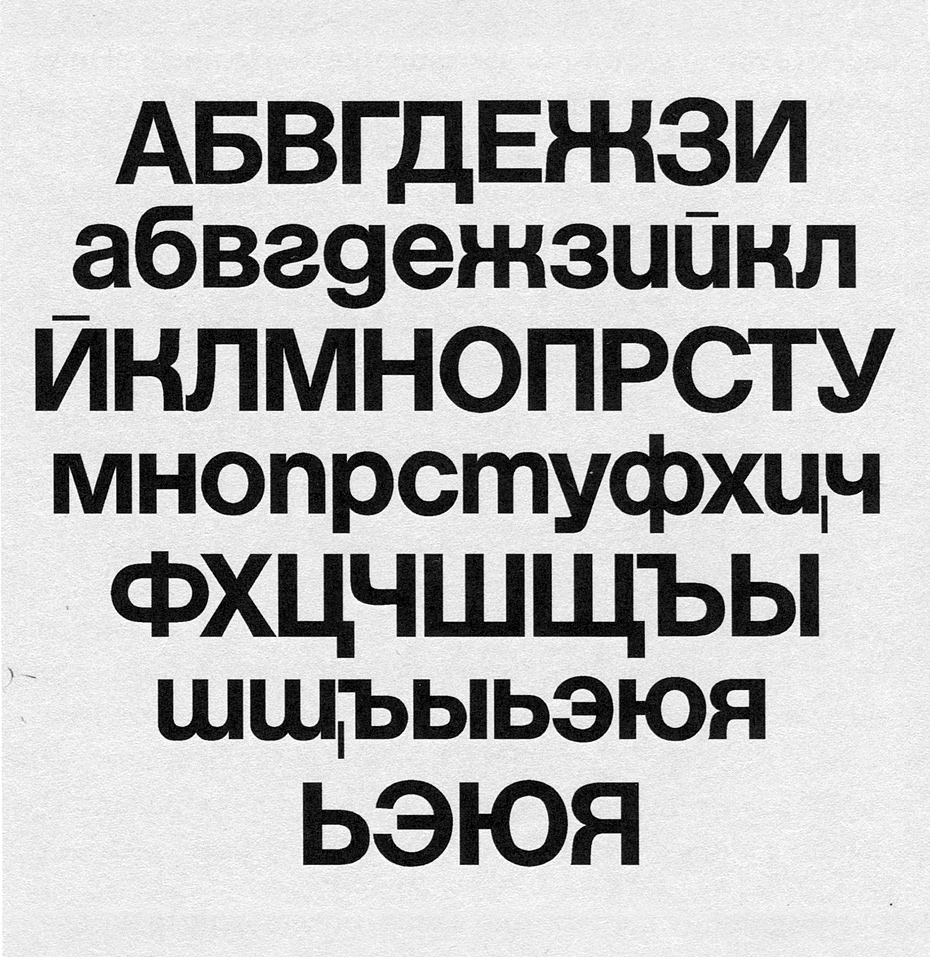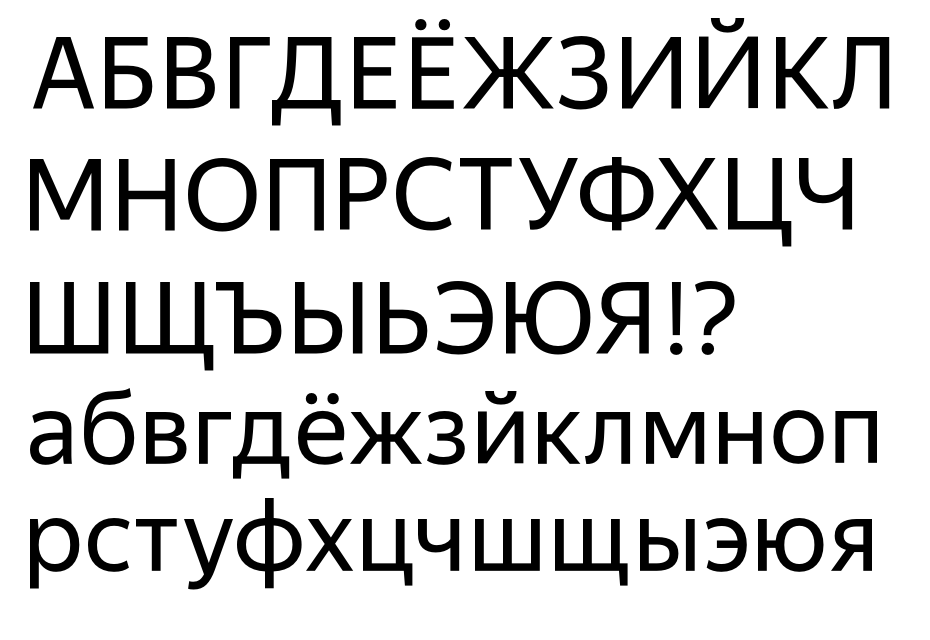
13 лучших шрифтов за эту неделю
Школа дизайна Uprock представляет подборку из 13 бесплатных кириллических шрифтов.
Timur Gusaruk
Lirica -— шрифт в стиле древнеславянских символов для дизайна исторических проектов. Узкие пропорции шрифта делают его идеальным для заголовков, логотипов, типографских композиций и коротких абзацев текста. Предназначен для личного использования.
FontCreator 9.0
Этот гротескный шрифт отлично подойдет для большого формата, например, для заголовков, дизайна логотипов, креативных агентств, плакатов, полиграфии.
gluk
Элегантный декоративный шрифт с засечками. Идеально подходит для заголовков проектов, которые хотят продемонстрировать свою изысканность и уникальность. Предназначен для личного и коммерческого использования.
Typodermic Fonts
Узкий гротескный шрифт с засечками. Подойдет для заголовков, дизайна логотипов, креативных агентств, модных брендов и любых нестандартных проектов, которые хотят привлечь к себе внимание. Предназначен для личного использования.
Alexey Atapin
Polonium — это современный дисплейный шрифт, вдохновленный историей открытия полония в 1898 году Мари и Пьером Кюри. Имеет обратный контраст и жирный шрифт. Предназначен для личного и коммерческого использования.
Maxim Raikov
Рукописный декоративный шрифт.
Идеально подойдет для любых нестандартных, креативных проектов, которые хотят выделиться на фоне других. Предназначен для личного и коммерческого использования.
Andrii Kurylo
Rebel Type Dog — это модульный дисплейный шрифт, который живет в жесткой сетке, но в нем есть доля человечности: некоторые модули пытаются нарушить правила, но они вынуждены оставаться частью этого мира антиутопии. Отлично подойдет для большинства проектов. Предназначен для личного и коммерческого использования.
Mariano Diez
Относится к категориям гротески, декоративные. За счет своей неординарности идеально подходит для заголовков, дизайна логотипов, смелых, нестандартных проектов, плакатов. Предназначен для личного использования.
Janusz M. Nowacki
Двухэлементный шрифт с грубыми, трассированными заглавными буквами и уникальными формами, которые могут обрабатывать множество стилей дизайна.
Относится к категориям гротески, декоративные. Изначально разрабатывался для набора газет и подобных периодических изданий. Отлично подойдет для любых проектов. Предназначен для личного использования.
Vova Egoshin Typemate
Отличный выбор для повышения значимости вашего проекта. Несмотря на традиционную типографику, основные элементы данного шрифта великолепны. Подходит для различных дизайнерских целей. Предназначен для личного и коммерческого использования.
Denis Ignatov
Старомодный декоративный шрифт с засечками, который пахнет Диким Западом и Клинтом Иствудом. Идеально подходит для заголовков, дизайна плакатов, логотипов и смелых, креативных проектов. Предназначен для личного и коммерческого использования.
Ksenia Semirova
Данный шрифт относится к категории декоративные.
Специально создавался для гламурных плакатов и глянцевых журналов, поэтому отлично подойдет для дизайна модных брендов, креативных агентств, дизайна логотипов. Предназначен для личного использования.
Raymond Larabie
Venus Rising — ультрасовременный шрифт квадратной формы с уникальным стилем. Отлично подходит для дизайна плакатов, логотипов, веб-графики, айдентики, игровой графики и многого другого. Предназначен для личного и коммерческого использования.
Что такое Типографика, какие бывают виды шрифтов, как научиться типографике?
Сайты, вывески и этикетки привлекают внимание зрителей не только яркими картинками, но и красивыми, удобными для чтения текстами. За создание вторых и отвечает типографика. Правильно подобранный шрифт является важным дополнением образа. А ошибки при его выборе могут перечеркнуть все впечатление.
Представляем вам полное руководство по типографике, из которого вы узнаете о видах шрифтов, их элементах, правилах использования и способах изучения.
Что такое типографика
Типографика — наука о шрифтах и технологиях оформления текстов. С ее помощью набор предложений превращается в красиво оформленную, удобную для восприятия текстовую информацию.
Один и тот же текст, может восприниматься совершенно по-разному. Именно типографика делает его привлекательным. Например, предложение «Привет всем, как выбрать шрифт?» может выглядеть так:
Kapra Neue Pro от Typoforge Studio — это суперсемейство из 96 гротескных шрифтов. Это длинный, вычурный гротеск, суперсовременный и привлекающий внимание. Благодаря широкому диапазону веса и ширины от сжатого до расширенного, Kapra Neue Pro является отличным выбором для брендинга, визуальной идентификации, веб-дизайна, упаковки продуктов, дисплеев, вывесок, плакатов, публикаций, логотипов, заголовков, редакционных статей и многого другого.